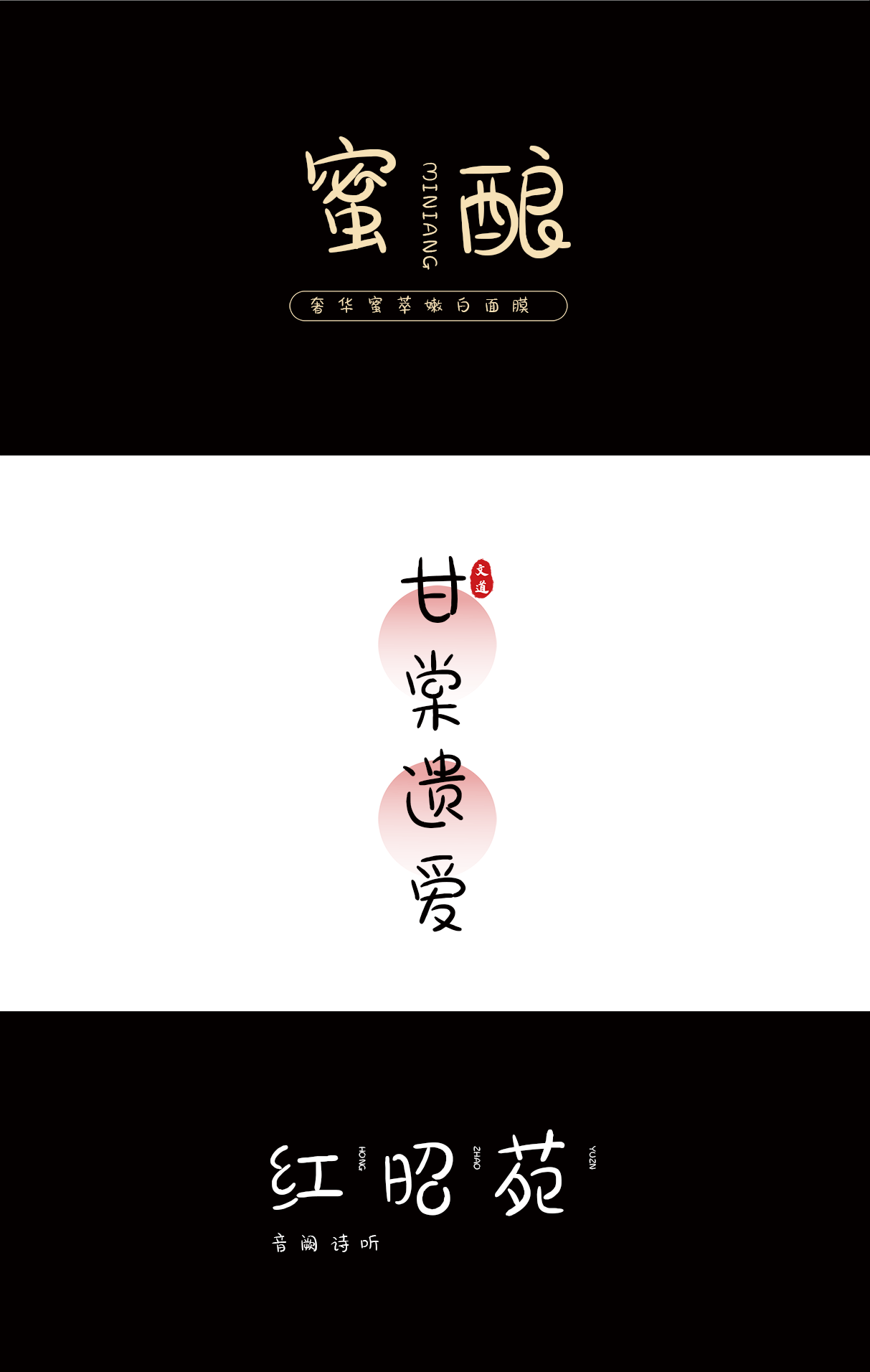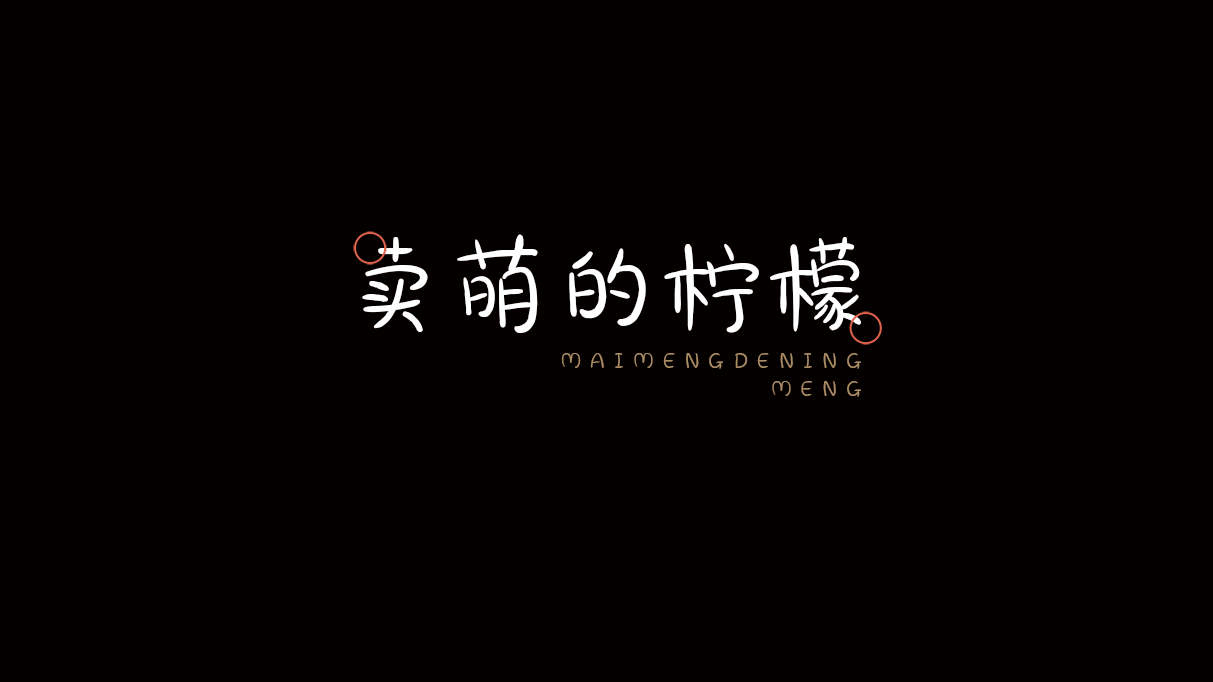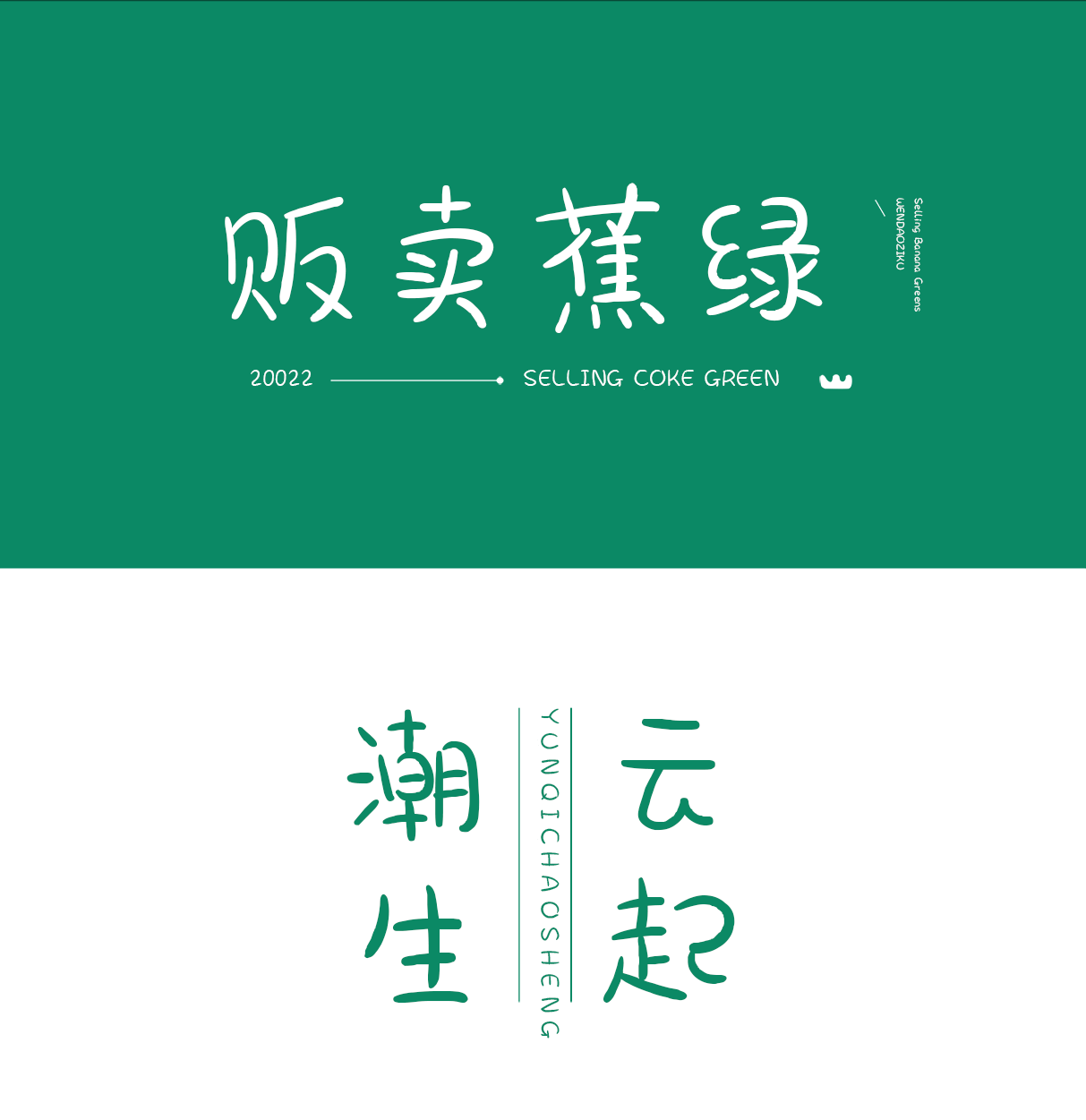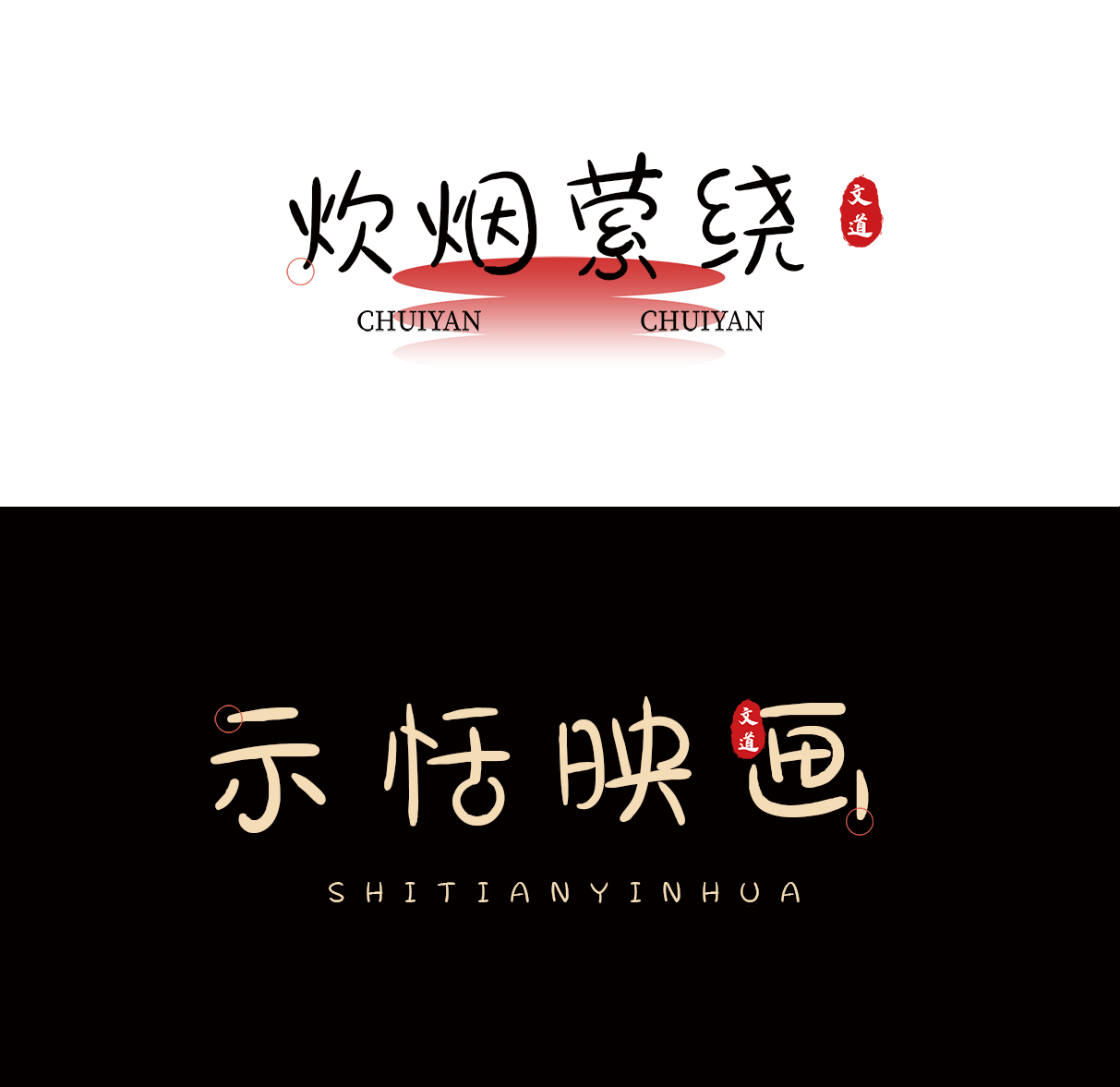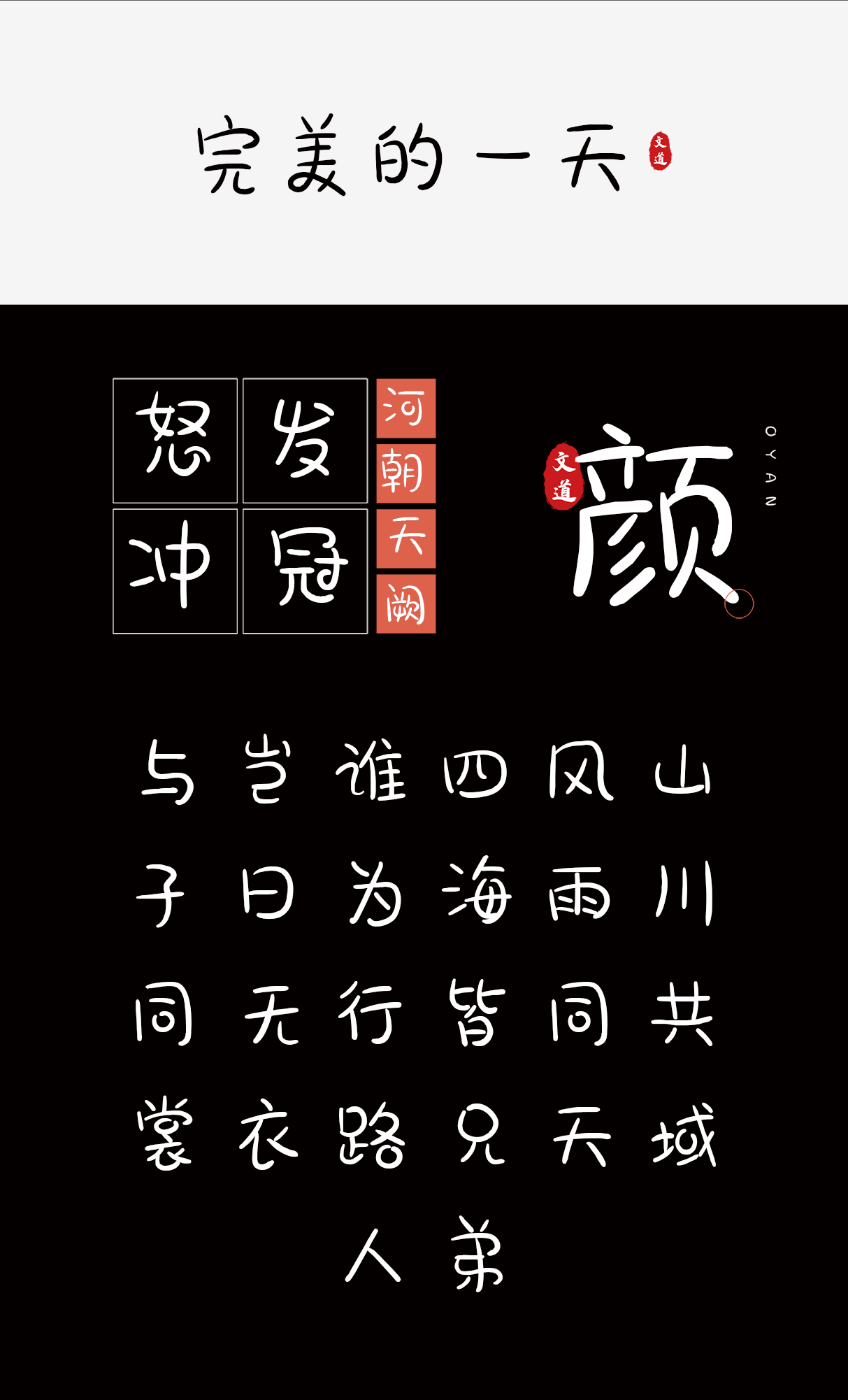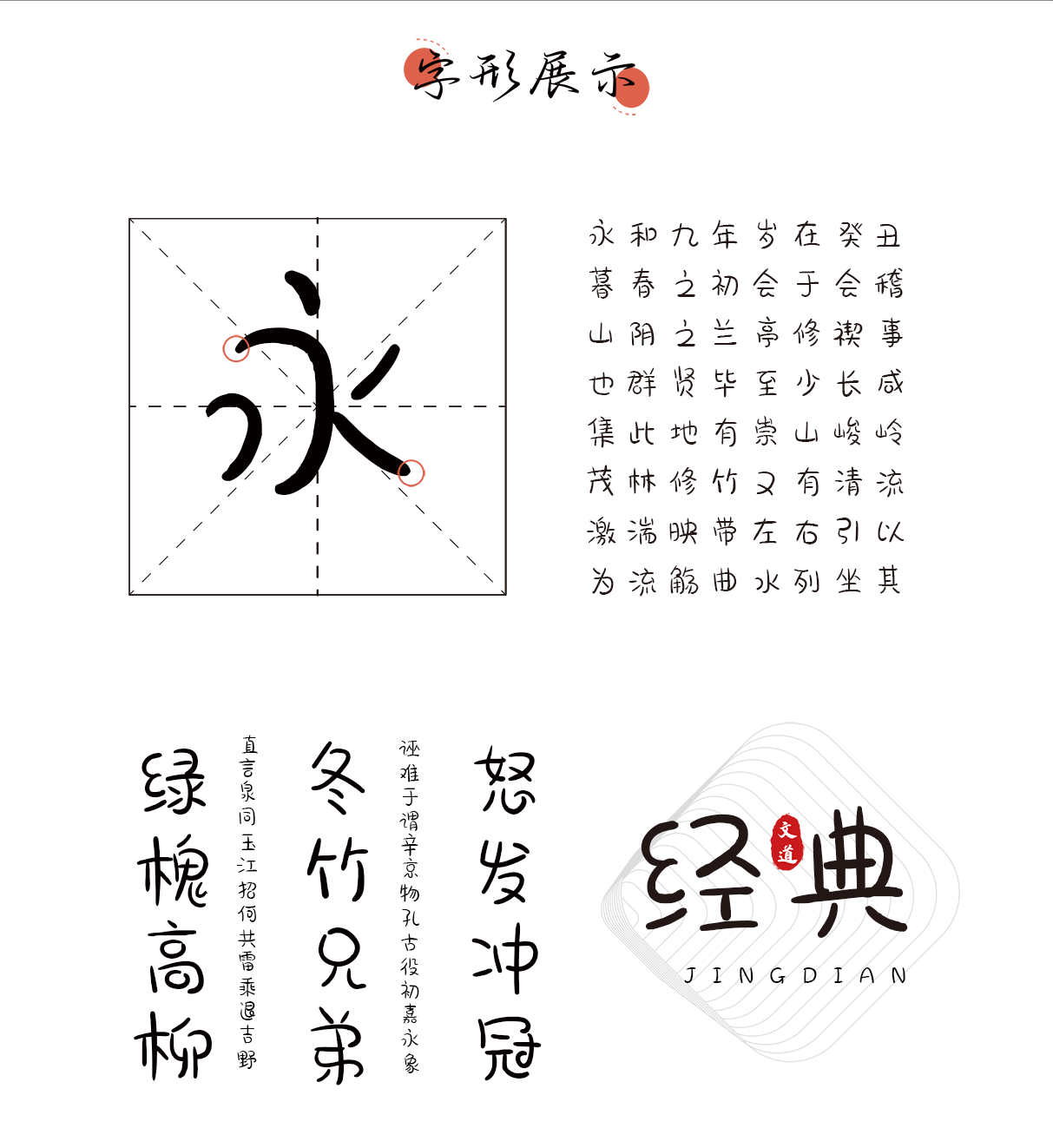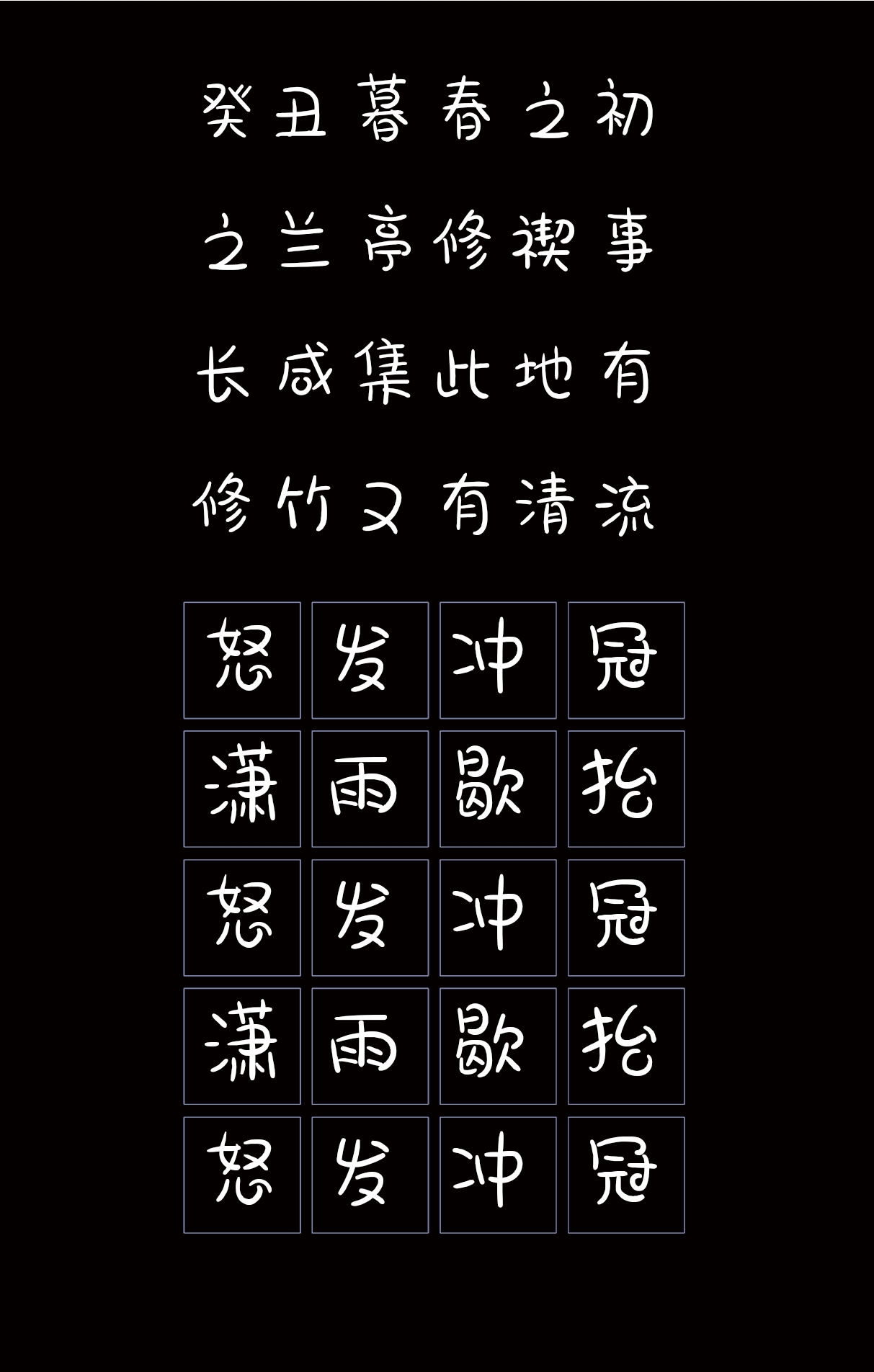
卖萌的柠檬
字体名称: 卖萌的柠檬
所属分类: 创意体 圆体
适用场景: 广告 游戏 电商 新媒 综艺 海报
简介: 【卖萌的柠檬】这是一款可商用创意体,圆滑的笔画,对于每一笔的粗细调整,一眼就觉得可爱滑稽的风格,该字包含6763个中文、字母、符号和数字,可用于印刷媒介的各类标题,字体风格正好适用于屏幕显示、广告标语和产品类包装设计。